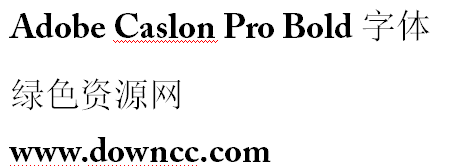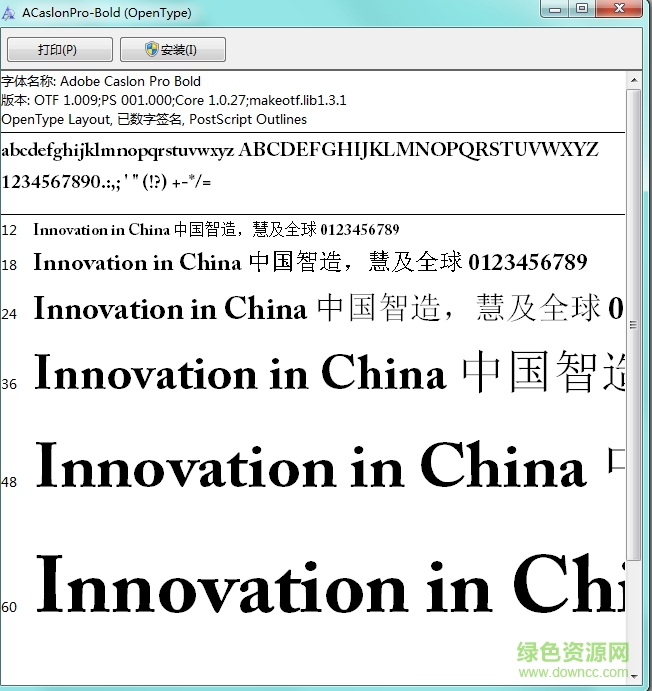
adobe caslon pro bold是一款加粗的常規(guī)西方字體,字跡簡明端正,加粗后讓字體更加鮮明吸人眼光,如果你對設計有比較高的要求,不妨來綠色資源網免費下載使用!
adobe caslon pro bold是adobe caslon系列字體中的加粗常規(guī)字體,有著大方得體、端莊嚴謹?shù)淖煮w風格,字體加粗后,讓英文書寫更加醒目,給人獨特的視覺好感,可廣泛運用于藝術設計、廣告創(chuàng)意、排版印刷、海報設計等各個方面。
adobe caslon系列包括Adobe Caslon Italic、Adobe Caslon Bold Oldstyle、Adobe Caslon Ornaments、AdobecaslonW01-Bd、AdobeCaslonW01-It、AdobeCaslonW01、Adobe Caslon Pro、AdobeCaslonW01-BdIt、Adobe Caslon Pro Italic、Adobe Caslon Pro等,adobe caslon pro是比較受歡迎的一款粗體。